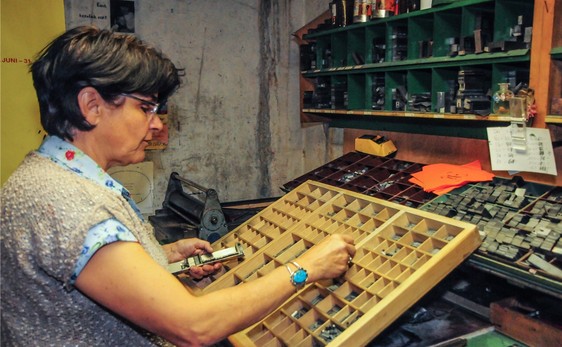
Literaturzeitschrift im Handsatz hergestellt
Mir deucht, Ihr reduziert grad den Bleisatz auf die Optik und vergesst die Haptik! Es rockt einfach, die Buchstaben fühlen zu können! Und das tut es auch noch, wenn ein Affe Comic Sans gesetzt hätte...
Keine Ahnung, ich meine das man es fühlen kann, dass es gedruckt (im Sinne von Drücken) wurde.
Da werden jetzt die geschätzten Kollegen Bleisetzer vermutlich entgegnen, dass man »richtig« im Bleisatz Gedrucktes nicht wie ein Prägung fühlen kann, weil es eben genau darauf ankommt, die Farbe mit dem richtigen Druck so auf das Papier aufzutragen, dass keine Verformung des Papier stattfindet.  :-) Ich hoffe, ich habe das als Druck-Laie richtig formuliert – wenn nicht bitte ich um Nachsicht und Korrektur.
Es gibt aber inzwischen beabsichtigten Prägedruck, zum Beispiel in ein weiches dickes Kartonmaterial mit extra dafür angefertigten Schriften (Bleisatzschriften gehen kaputt, wenn man zu viel Druck einsetzt). Wenn ich mich richtig erinnere, dann gibt es hier in der Forums-Werkschau Arbeitsbeispiele von Martin Z. Schröder zum Thema Prägedruck.
Korrekt Kathrin. Genau das machen viele dieser selbsternannten "Letterpress" Drucker.
Na, das macht Kollege Martin Z. Schröder aber auch und gibt es selber zu – steht im TJ4 (meine ich)  :nicken:
Wenn man ein Kind ein Bild kritzeln sieht, schüttelt man ja auch nicht den Kopf und meint, es solle erstmal eine richtige Ausbildung durchlaufen. :-)
Naja, die Dame ist kein Kind, sondern eine Erwachsene, die sich auf den Marktplatz der Öffentlichkeit begeben hat.
Ich denke schon das Bleisatz heute wieder etwas besonderes ist. Im Kontext einer selbst verlegten und selbst gedruckten Zeitschrift auf jeden Fall.
Ja, da bin ich durchaus deiner Meinung.
Aber wenn du meinen Beitrag genau liest, wirst du das Wörtchen „alleine“ vor dem Wort Bleisatz lesen.
Ich schrieb ja
Und Bleisatz ALLEINE ist eben nichts Besonderes.
Bleisatz gut gesetzt und gestaltet ist sicher etwas Besonderes. Aber nur weil Bleisatz zur Anwendung kommt, heißt das nicht, dass hier eine besondere Arbeit vorliegt.
»Die Letter darf das Papier nur küssen«, erklärt der Buchdrucker. Und wenn ein Buchdrucker den andern besucht und sich eine Arbeit anschaut, dann prüft er gern die sogenannte Schattierung auf der Rückseite einer Drucksache. Wenn da gar nichts zu sehen ist, zieht er seinen Hut. Das hat zwei Gründe: Der erste: Je weniger die Schrift geprägt ist, desto klarer ist ihr eigentliches Bild zu sehen, somit auch ihre Qualität, die nicht durch Quetschränder gemindert wird. Der zweite Grund: Wenn Bleischriften geprägt werden, nutzen sie sich sehr schnell ab, und da neue Bleischrift einen Haufen Geld kostet, will ihr Besitzer sie in der Regel schonen, damit er lange damit auskommt.
Das war aber nicht immer so. In Büchern auf Dünndruckpapier des 20. Jahrhunderts findet man oft eine recht starke Schattierung. Wenn sie von maschinell hergestelltem Satz (Linotype-Zeilen oder Monotype-Lettern) gedruckt sind und man die Schrift ohnehin wieder einschmilzt, gibt es keinen wirtschaftlichen Verlust für die Druckerei. Und wenn exakt registerhaltig gedruckt wurde, beeinträchtigt es die Ansicht von Schön- und Widerdruck kaum. Und in alten Büchern ebenfalls. In der mittelalterlichen Druckerei wurden die Papierbogen befeuchtet, damit sie sich ordentlich um den Druckstock legen und ihn gut abbilden können. Anschließend hat man die Bogen nach dem Trocknen durch die Mangel gedreht, denn die Prägung galt nicht als schön, zumal in Büchern, wo sie auf der jeweiligen Rückseite, die ja auch bedruckt ist, die Schönheit des Bildes stört. In Antwerpen habe ich gerade vor ein paar Tagen im Museum Plantin Moretus ein Buch gesehen, 1523 gedruckt, stark schattiert, im Druck nicht zugerichtet und sehr unsauber. Es gab ja damals auch noch keine Walzen, man hat mit Tampen eingefärbt. Und doch ist das anrührend schön, denn die Typografie siegt über die Schwächen der noch jungen Technik. Und zumal wenn man in den Nebenräumen gerade die Stahlstempel, die Kupfermatrizen und die Gießerei besichtigt hat, dann will man als Buchdrucker fast niederknien.
Aber die Moden wechseln, und zur Zeit wird der Prägedruck auf rauhes Material von den meisten Leuten als schön empfunden. Es ist offenbar ein angenehmer Gegensatz zu den glatten kalten Oberflächen der technischen Gerätschaften, mit denen man unentwegt zu tun hat. Ich drucke so etwas gar nicht ungern. Prinz Asfa Wossen-Asserate hat es in seinem Manierenbuch getadelt, wenn Menschen einen Stahlstich befingern, um sich an den erhabenen Buchstaben zu ergötzen und den ungeprägten unauffälligen Bleisatz zur feinsten Art des Druckes erklärt. Ich muß sagen, daß ich diesem Reiz auch jedesmal erliege, wenn ich einen gutgemachten Stahlstich in der Hand habe. Einerseits mag ich das Wort »Haptik« gar nicht mehr hören, weil es eben der Kennerschaft gegenübersteht. Andererseits finde ich sowohl Blindprägungen mit ihren Schattenwürfen als auch eine sauber geprägte gute Schrift wirklich schön. Ich habe mich ein paar Jahre gegen den Prägedruck gewehrt, aber dann doch damit angefangen, und jetzt halte ich ihn für durchaus legitim. Als Distinktionsmerkmal unter Bildungsbürgern kann er allerdings heute nicht dienen, das merke ich den Kennern unter meinen Kunden immer wieder an: Bloß keine Prägung! Das wird als billiger Protz empfunden. Ich kann mich zu einer so klaren Meinung nicht durchringen. Ich drucke beides gern, wenn es gute Entwürfe sind. Ich kann auch den nach der reinen Lehre schlecht zugerichteten und mangelhaft eingefärbten Holzlettern etwas abgewinnen.
Der Bleisatz ohne Schattierung wird in meiner Werkstatt von Menschen gewünscht, denen man Kennerschaft zuschreiben kann. Kunstkenner und Bibliophile. Ihnen geht es nicht um den vordergründigen Effekt, sondern um die nur für eben Kenner sichtbaren feinen Ungleichmäßigkeiten einer schönen Schrift in einem sauberen Entwurf. Die Farbgebung ist im Buchdruck anders, sie läßt die Drucksache lebendiger wirken als Drucksachen aus der Offset- oder Digitaldruckmaschine. Unter der Lupe kann man die feinen Unregelmäßigkeiten dann erkennen. Diese Art Kennerschaft als Distinktionsmerkmal gibt es überall: echte Maßanzüge, handgemachte Schuhe und Möbel oder Platinschmuck erkennt in der Regel nur, wer selbst so etwas besitzt und den Handwerker bei der Arbeit ein Stück begleitet hat.
Die in der Zeitung vorgestellte Druckerin scheint all solchen Fragen fernzustehen. Ich habe dazu nur eine kurze Anmerkung gemacht, so wichtig, daß sich daran ein Disput entzünden könnte, habe ich das nicht genommen.
Man kann solchen Arbeiten durchaus einen kindlichen Charme zugestehen:
Aber Erwin Krump hat es ganz richtig gesagt: Durch solche Veröffentlichungen und auch den uneingelösten Anspruch auf künstlerischen Wert, der aus der Website der Verlegerin hervorgeht, wird das ganze Handwerk in die Hobby-Ecke geschoben.
Ob man Lokalzeitungen immer für quasi naturgegeben minderwertig halten muß, bezweifle ich. Zur Zeit gibt es vielleicht keinen guten Lokaljournalismus in gedruckten Zeitungen. Ich kenne zu wenige, um das beurteilen zu können. Aber es gab erfolgreiche Versuche wie die »Berliner Seiten« der FAZ, auch unsere engere örtliche Lebenswelt journalistisch erstklassig und auch feuilletonistisch zu begleiten. Und ein Online-Magazin wie die Prenzlauer Berg-Nachrichten kann diesen Anspruch sogar gegenwärtig einlösen.
… Frauenfeld in der Schweiz (Anfang November) …
Da wirst Du auch Gianna finden ... höchstwahrscheinlich. Zumindest war sie die letzten Jahre immer auf dieser Messe.
Otto-Arialverbraucher